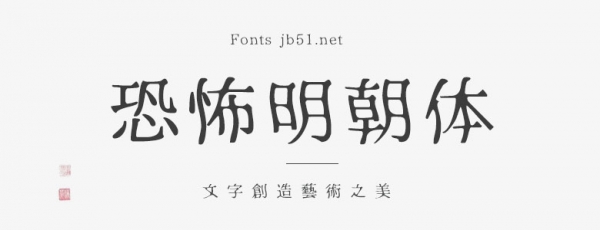
恐怖明朝體(07ふぉんとうは怖い明朝體/07ReallyScaryMinchotai)是一款來自日本的免費字體,它可以用于商業(yè)和非商業(yè)目的。
恐怖明朝體是一種奇怪的字體,帶有輕微破碎的印象。想象一下一個典型的日本恐怖電影/恐怖小說,但是由您決定該字體是恐怖還是輕柔。
雖然是來自日本的字體,但是該字體對中文的支持還是不錯的,簡體有缺字現(xiàn)象,繁體支持得比較好,究竟怎么樣下載試試吧!